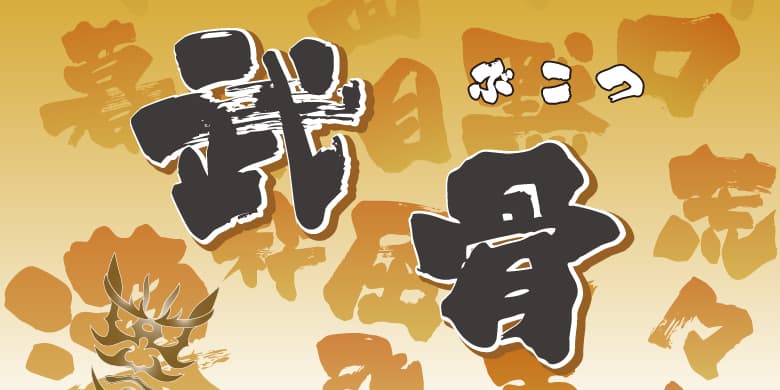
方正白舟武骨体的个性沉默、安静、天真、狂野、憨直、粗暴、倔强,代表男性的形象。这是一款中宫紧凑的方形字体,笔画粗壮有力,乍看之下像是一个不太成熟的未成年人,同时又呈现出一种稳健自若的精神面貌。运用枯笔书写出来的白舟武骨飞白鲜明、坚固厚实,给观者以一种倔强粗犷的印象,适用于大字招牌,和传统文化类的标题、短语这种需要视觉具有冲击感的场景。